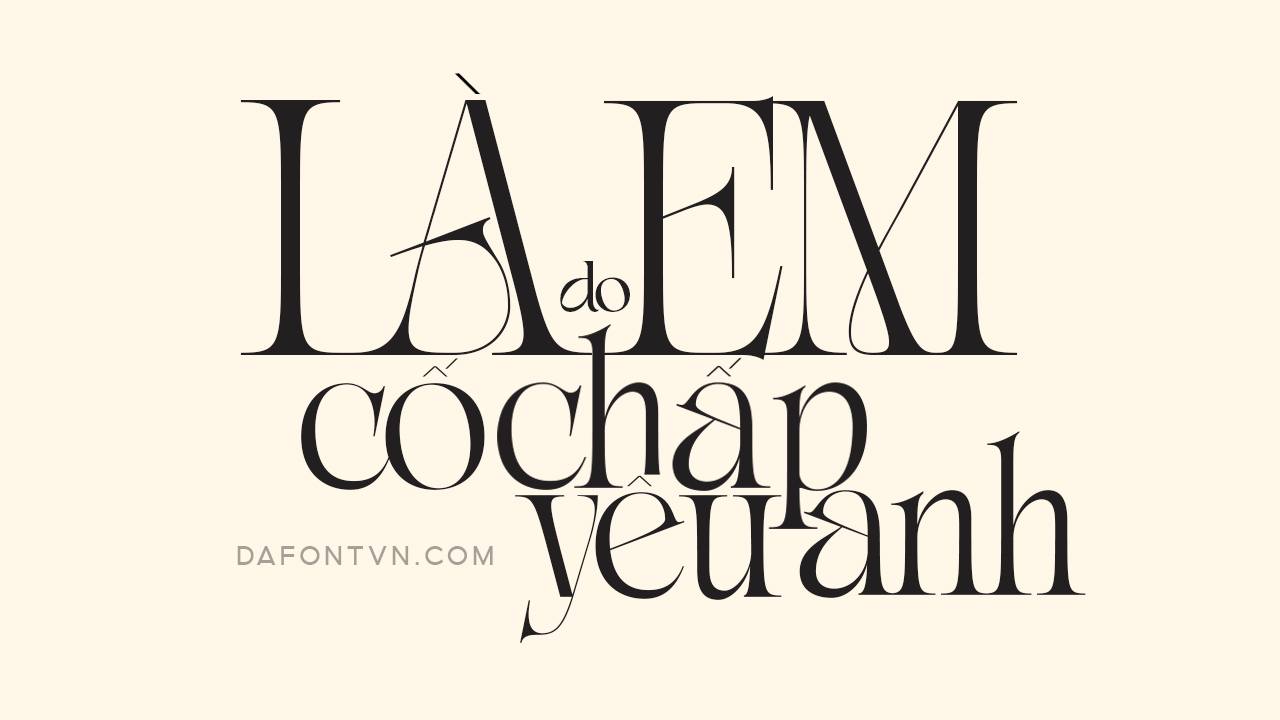
Font Fashion Wacks – 1 kiểu font serif hiện đại lấy cảm hứng từ Art Nouveau (Tân thời đại) mang phong cách nghệ thuật đặc biệt là nghệ thuật trang trí với một vẻ đẹp rất ấn tượng và thời thượng.
Nếu bạn đang tìm kiếm một kiểu font hiển thị ấn tượng thì Fashion Wacks là font bạn không thể bỏ qua, Fashion Wacks mang đến sự hài hòa về kiểu chữ đẹp mắt cho nhiều dự án thiết kế khác nhau, bao gồm logo, typography, thiết kế sản phẩm, bìa sách…
Font Fashion Wacks mang đến những ấn tượng riêng vì vậy bạn hãy thử thiết kế biến hóa theo ý tưởng của mình nhé. Font được việt hóa đầy đủ, chỉnh sửa, tối ưu cũng như kerning.